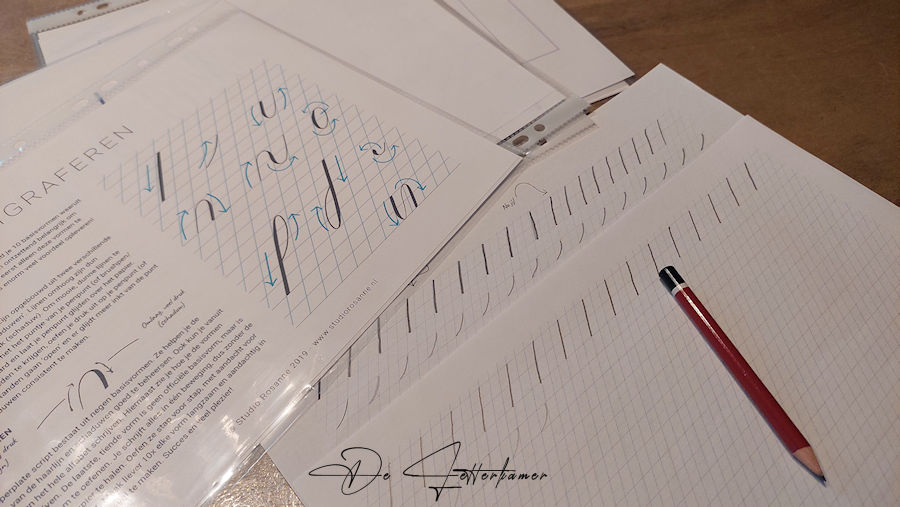
Ik wilde het eens hebben over de oefenbladen:
Copperplate werd altijd geschreven in een schuinte van 55°. Om zo te leren schrijven, kan men beter oefenbladen downloaden en printen. Men kan ook oefenboeken kopen, daar zijn er een paar voorbeelden van letters en basisvormen die je kan overschrijven. Zo heb je de handeling om in de schuine richting te schrijven in een vaste graad. Zeer handig! Het blad mag je tussen de 30° en 45° draaien tegen de klokrichting in. Tot het natuurlijk aanvoelt om te schrijven.
Wat zijn nu de typische kenmerken van Copperplate (Een Engels rondschrijft: English Round Hand)
• sterk contrast tussen dunne en dikke lijnen
• zeer dunne haarstreken
• schuine, cursieve letters
• ronde, elegante vormen
• veel lussen en krullen
• een vaste schuinte, vaak rond 55°
• geschreven met een puntige flexibele pen
• dikke lijnen ontstaan door druk op de pen, dunne lijnen door weinig of geen druk
Dit is het oefenboek dat ik heb:
Deze week ga ik verder oefenen, van zodra de avond valt, komt mijn pen tevoorschijn.